Dalam desain grafis setiap style elemen dapat menciptakan tema dan kesan yang berbeda sehingga digunakan untuk kebutuhan berbeda. Perhatikan bagaimana setiap gaya font akan digunakan untuk kebutuhan berbeda, untuk itu perlu memilih jenis yang tepat. Contohnya pada penggunaan font script yang unik digunakan untuk kebutuhan jenis desain tertentu.
Font script sendiri adalah font yang memiliki gaya huruf menirukan tulisan tangan sehingga menciptakan kesan alami. Jenis desain yang cocok dengan font script biasanya menyesuaikan style font agar terlihat relevan. Style script yang berbeda akan menciptakan kesan berbeda dan dapat digunakan untuk tema desain yang berbeda.
JENIS STYLE FONT SCRIPT
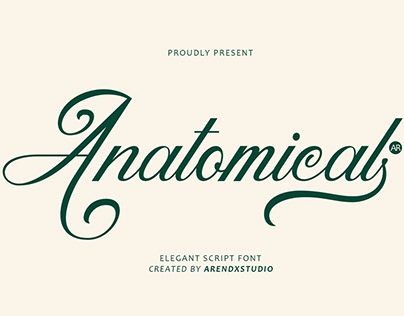
Jenis style font script biasanya ada yang latin, handwritten, dan brush, selain itu divariasikan tebal dan tipisnya. Untuk setiap style tersebut akan digunakan untuk kebutuhan berbeda. Namun umumnya akan menciptakan kesan seperti:
- Script Latin Tipis: Menciptakan kesan elegan dan mewah, karena memiliki guratan garis yang lembut.
- Script Latin Tebal: Jenis font tebal ini biasanya cocok untuk script yang memiliki keterbacaan yang baik.
- Brush Script: gaya font brush yang juga mengikuti gaya tulisan tangan terlihat alami, dan bisa menciptakan kesan autentik dan estetik. Beberapa font brush yang bertekstur bisa menciptakan kesan horor atau usang.
- Handwritten Script: Bedanya ini dengan script Latin adalah gaya hurufnya yang tidak rapi dan agak berantakan seperti tulisan tangan. Font ini lebih efektif menciptakan kesan alami dan cocok untuk menciptakan kesan ramah.
Pastikan untuk menggunakan style font script sesuai kebutuhan agar tampil menarik dan mencerminkan pesan dengan baik. Penggunaan font script tidak bisa digunakan untuk semua jenis desain sehingga perlu disesuaikan kebutuhan dan temanya.
JENIS DESAIN YANG COCOK DENGAN FONT SCRIPT
Untuk menggunakan font script dalam desain grafis, pertimbangkan jika desain ingin tampil unik, elegan, dan alami. Dalam penggunaannya font script banyak digunakan untuk font judul dan headline sehingga mudah terbaca. Pada ukuran kecil mungkin akan sulit dibaca karena bentuk hurufnya yang unik. Berikut beberapa jenis desain yang sering menggunakan gaya font script:
Desain Undangan Pernikahan
Untuk jenis font script Latin yang tipis, penggunaan fontnya akan menciptakan tampilan yang elegan dan mewah. Gaya font ini akan cocok digunakan sebagai font utama dalam desain undangan pernikahan. Font yang elegan akan menciptakan kesan formal, sakral dan indah.
Pada desain undangan pernikahan font script yang tipis dan latin bisa digunakan sebagai font teks nama. Agar menarik pilih jenis font script yang mudah dibaca, terkadang beberapa font script patin terlalu panjang dan berbentuk aneh. Biasanya dalam desain undangan font script yang elegan akan dikombinasikan dengan font serif yang elegan juga agar harmonis.
Desain Konten dan Poster Natal atau Winter
Gaya font script elegan dan cocok untuk mencerminkan kesan elegan pada berbagai desain termasuk tema natal dan winter. Jenis font script yang cocok untuk tema natal dan winter adalah font script yang latin dan brush. Font latin yang cocok bergaya agak tebal sehingga tampil lebih ramah dan elegan.
Jika diperhatikan biasanya desain poster dan konten bertema natal akan tampil elegan sehingga cocok menggunakan font script. Sementara itu tema winter sendiri font script latin dan brush akan cocok menciptakan kesan alami. Font brush yang memiliki tekstur agar tampil harmonis dengan desain bertema musim dingin.
Desain Logo Mewah
Gaya font script yang alami mengikuti tulisan tangan bisa menciptakan kesan alami dan mewah terutama dengan garis huruf yang tipis. Penggunaan font script juga banyak digunakan untuk logo mewah dan elegan seperti untuk kebutuhan brand fashion dan kecantikan.
Logo terkenal dunia seperti Cartier juga menggunakan gaya font script latin yang tipis sab bergaya elegan. Pada desain logo kesan mewah yang diciptakan dari font script akan membantu membuat brand tampil tepercaya dan high-end brand. Terkadang font script juga banyak ditemui dalam desain logo makanan seperti bakery.
Desain Poster Horor
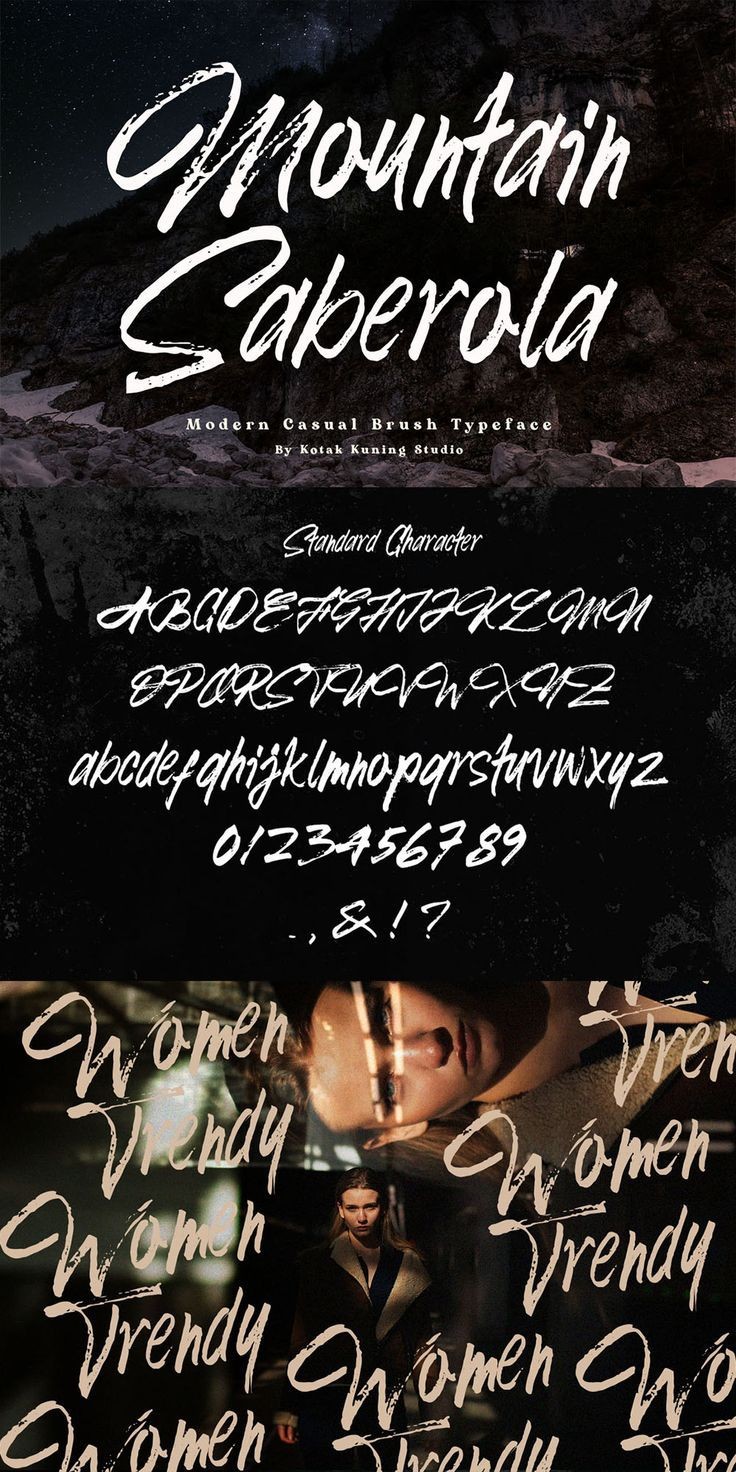
Penggunaan font script juga bisa digunakan untuk tema desain poster yang horor atau untuk tema halloween. Biasanya tema horor akan menggunakan gaya font yang unik dan menciptakan kesan horor atau misterius. Gaya font brush script bisa menjadi pilihan karena memiliki karakter guratan kasar dan tekstur pada fontnya.
Efek guratan brush yang kasar pada font tersebut bisa menciptakan kesan horor dan misterius. Font brush dalam desain poster horor akan cocok dengan warna merah atau hitam untuk menciptakan kesan misterius. Guratan brush script membuatnya cocok digunakan dalam poster bertema horor dan halloween.
Berbeda jika menggunakan font brush yang tidak bersambung, gaya huruf yang tebal masih akan terbaca dengan baik. Jika ingin dibuat tebal, pertimbangkan ketebalan yang proporsional yang membantu teks tetap terbaca dengan baik.
Font script merupakan font yang mengikuti bentuk tulisan tangan dan memiliki gaya huruf handwritten dan brush. Gaya huruf script yang bersambung dan style tipis cukup populer untuk menciptakan tampilan elegan. Penggunaan font script harus bijak dan sesuai jenis desain sehingga tampil harmonis.